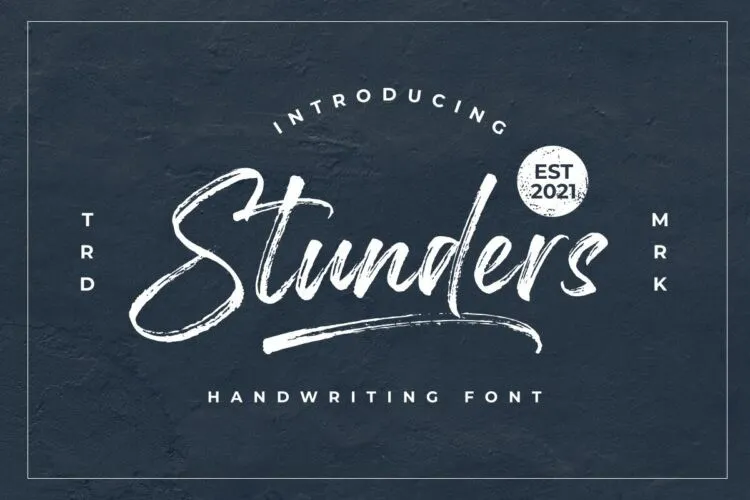
Stunders Font – Download Grátis
A Stunders Font é uma opção incrivelmente versátil para designers apaixonados por texturas elaboradas e efeitos rústicos. Fabricada pela Ghuroba Studio, esta fonte script traz um contraste alto entre os traços finos, aliado a um tom desenhado ao acaso que adiciona um toque único à sua composição. Suas características incluem uma inclinação e uma tipografia divertida, tornando-a perfeita para diversas aplicações gráficas. Esse estilo é ideal para criar marcas de marca ou logotipos com personalidade, embalagens de produtos que valorizem a criatividade, cartões de aniversário, mensagens de referência, e muito mais. Com a Stunders Font, você pode transformar qualquer design em algo realmente único, repleto de vida e entusiasmo. Aproveite para explorar o poder da fonte e faça seus projetos brilharem ainda mais!